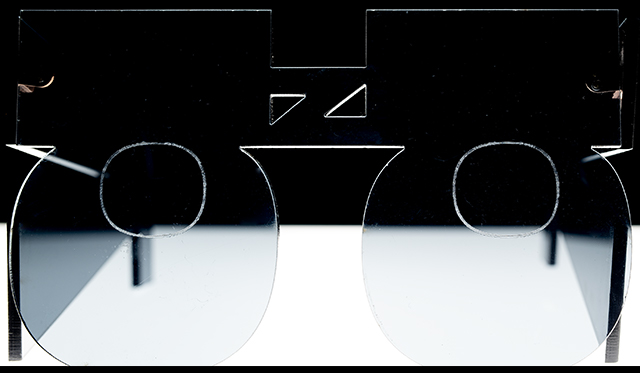
ANTIQUE OLIVE
Das Auseinandersetzen und intensive Beschäftigen mit einer favorisierten Schriftfamilie, war Aufgabe im 2. Semester Typografie. Besonderheiten erkennen, die einzelnen Schnitte in ihre Details zerlegen, bis simple geometrische Formen übrig bleiben.
Gedanken und Entwürfe in ein Exponat zu überführen, um dies bei der Werkschau 2019 zu präsentieren, war ebenfalls Teil der Aufgabe. Ich entschied mich für Brillen und Sonnenbrillen, die aus dem Alphabet und den einzelnen Schnitten der Antique Olive entstehen sollten. Diese wurden aus schwarzem, weißem und orangenen Acrylglas gelasert. Mit Optiker Harzer baute ich eine Brille gemeinsam zusammen, um anschließend die restlichen Brillen in der Klasse für Schmuck und Gerät an der Akademie der bildenden Künste Nürnberg anzufertigen.